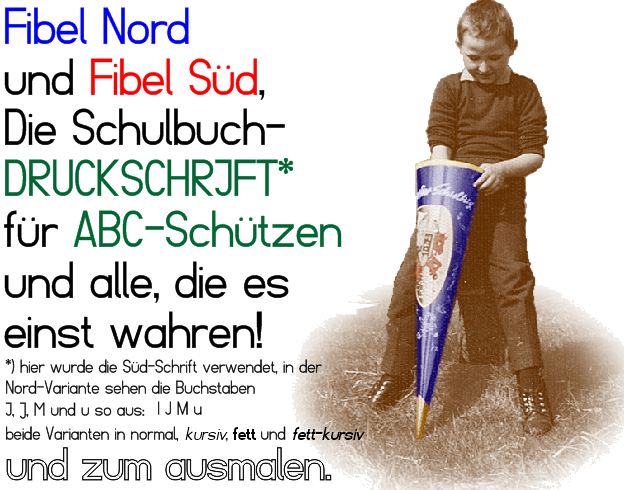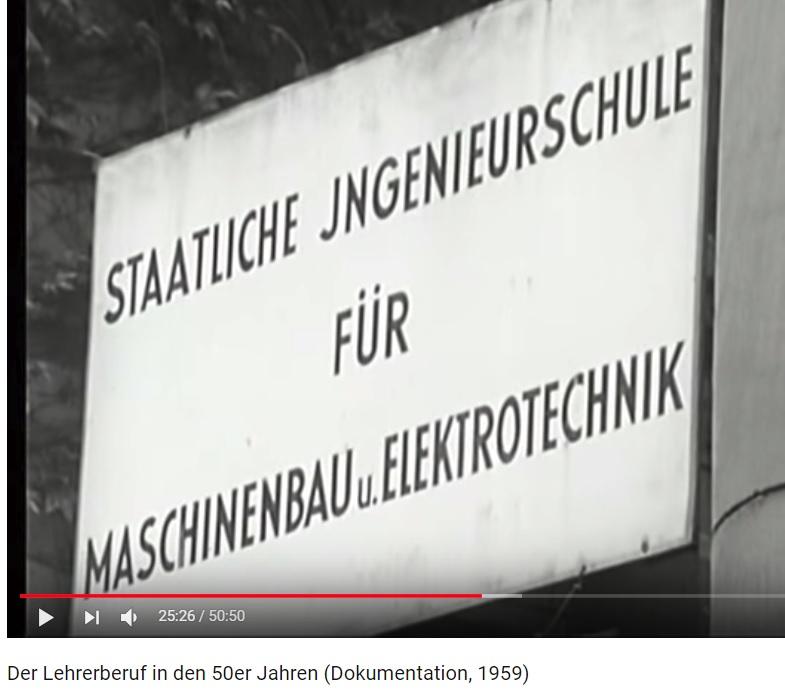
Aus einem YouTube-Video über Lehrer in den 50ern.
Es gab damals ja auch das Radio JMPERIAL, das sozusagen beide Formen des großen „I“ in der Aufschrift vereinte. War das eine gängige Praxis?
beide Formen des großen „I“ in der Aufschrift […] War das eine gängige Praxis?
Nö. Aber offensichtlich war es eben auch nicht völlig unmöglich/unverständlich. Halt ein Schmuck-I für den Wortanfang.
Und was diese Sache mit dem stellungsabhängigen  J / I Allograph anbelangt, kann ich mich an meine ABC-Schützen Zeit und noch etwas danach, die ja in die angesprochene Zeitperiode fällt, aus dem Stadtbild deutlich erinnern, dies auch auf diversen Ladenschildern, Fahrzeuganschriften und Leuchtreklamen gesehen zu haben. Ich erinnere mich, dass ich mich bei Worten die eigentlich mit einem I beginnen als ersten Buchstaben ein J verwendet, besonders wenn der ganze Firmenname in Großbuchstaben geschrieben war und im Inneren dann ein I verwendet wird.
Gut möglich, dass es hier nie eine offizielle Regel gab, Schildermaler, Autobeschrifter und Leuchtreklame-Hersteller dies trotzdem so von einander abgeguckt haben, weil ein mit einem I beginnendes Wort einfach nicht sonderlich schön aussieht. I ist wohl einfach zu schlank im Wortanfang.
Ich habe mich in den 80ern als Kind auch über ein grünes Schild vor einer Brücke gewundert, auf dem JSAR stand. Wo das war, weiß ich nicht mehr, sonst würde ich nachschauen,  ob es immer noch so geschrieben ist.
Ich habe ja auch die beiden wesentlichen deutschen Fibelschriften als Fonts erstellt, also eine Nord- und eine Südversion. In der Süd-Version sind die Formen von I und J anders: (PS, der mit der Schultüte bin ich)
Ach ja, zur eigentlichen Frage hier:  Ich habe mir da mal was für reine Versalschriften überlegt, so zu sagen ein "großes Versal-I" und ein "kleines Versal-I"
Ist Fahrtwindserife eigentlich der korrekte Fachbegriff? ☺️
Beim letzten Probenwochenende „entdeckt“:
Spannende Serifenformen im Titel und das S scheint das A nicht besonders zu mögen ;-)
war sicher Teufelswerk … ;-)